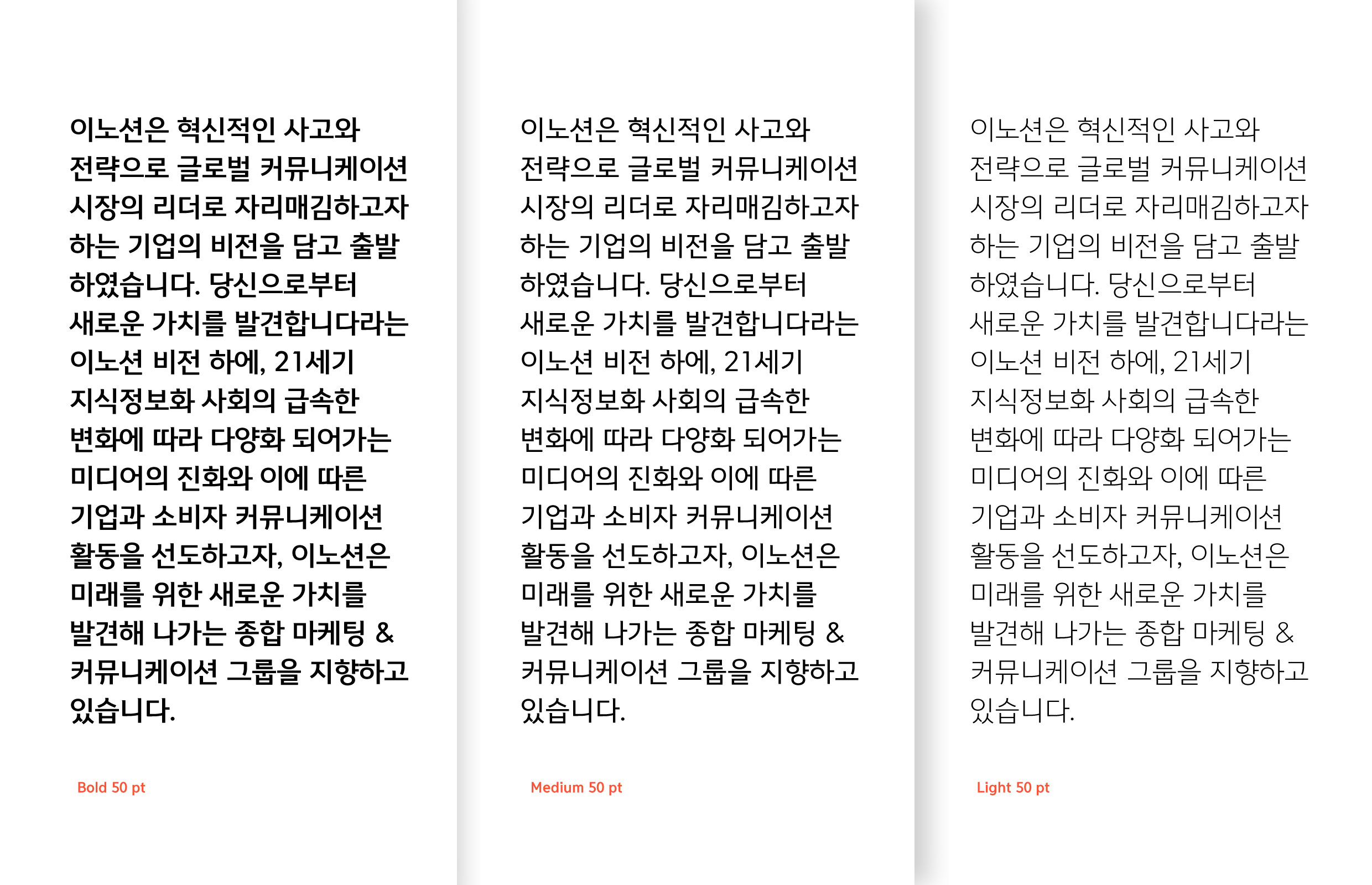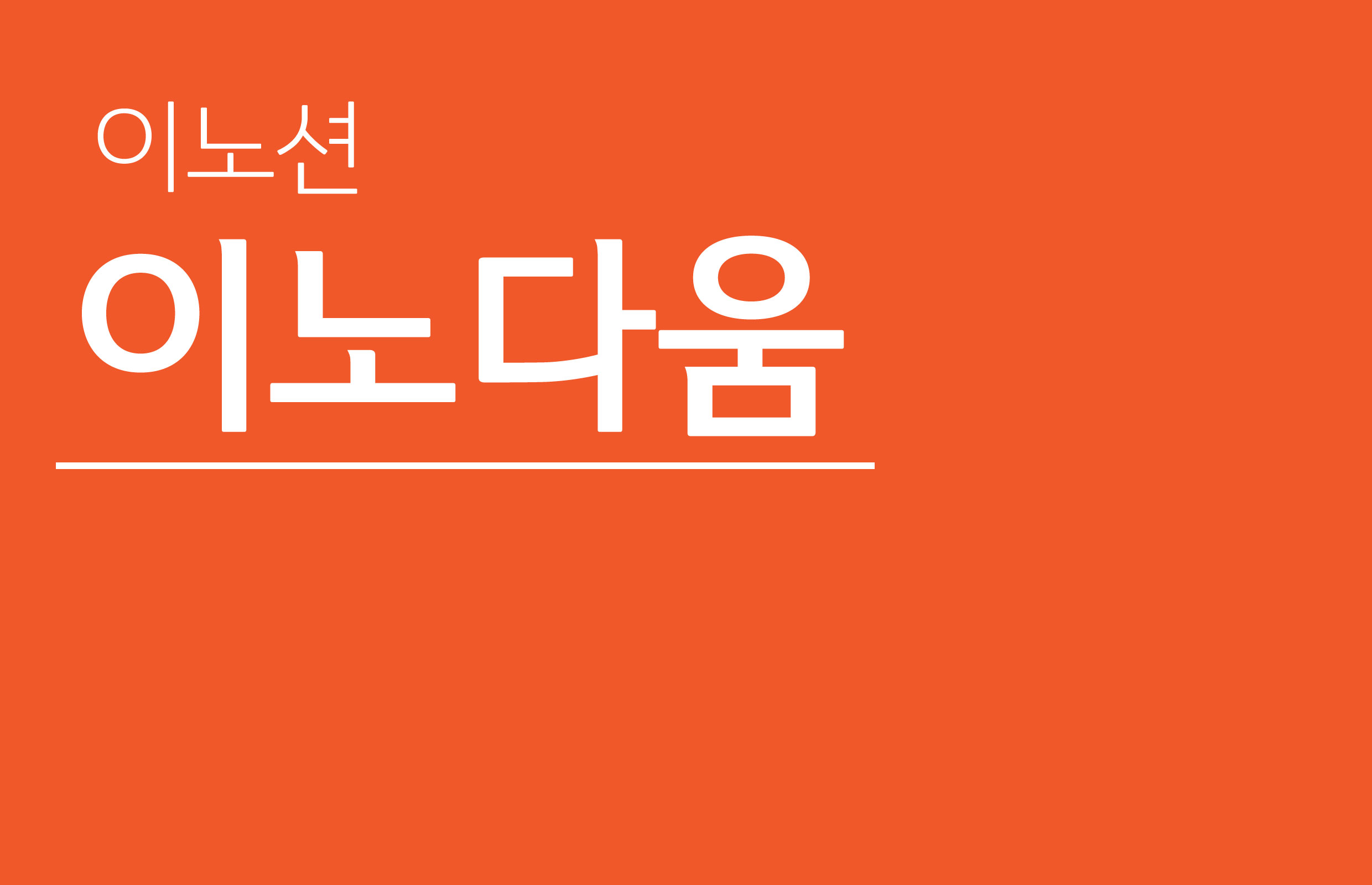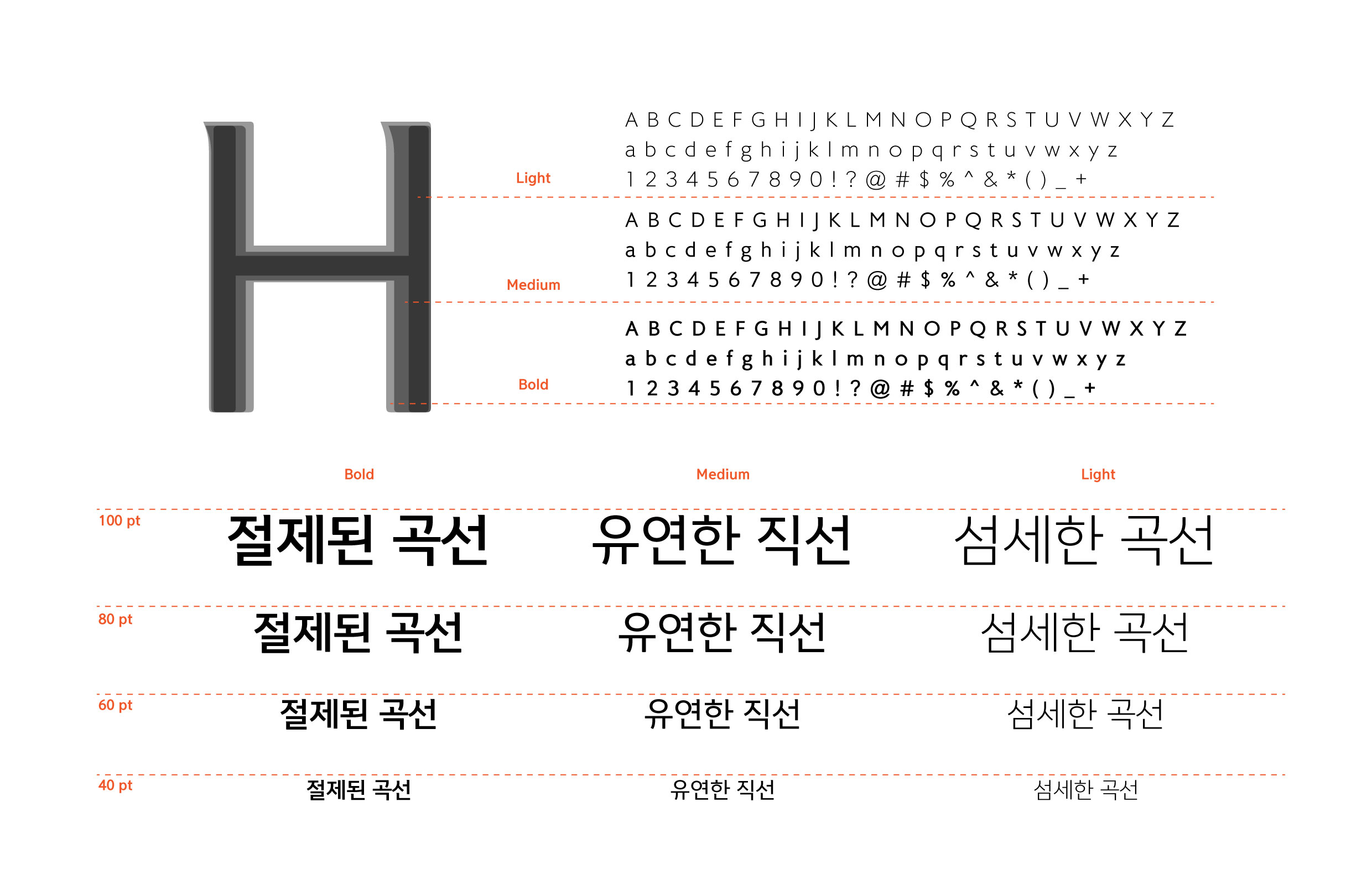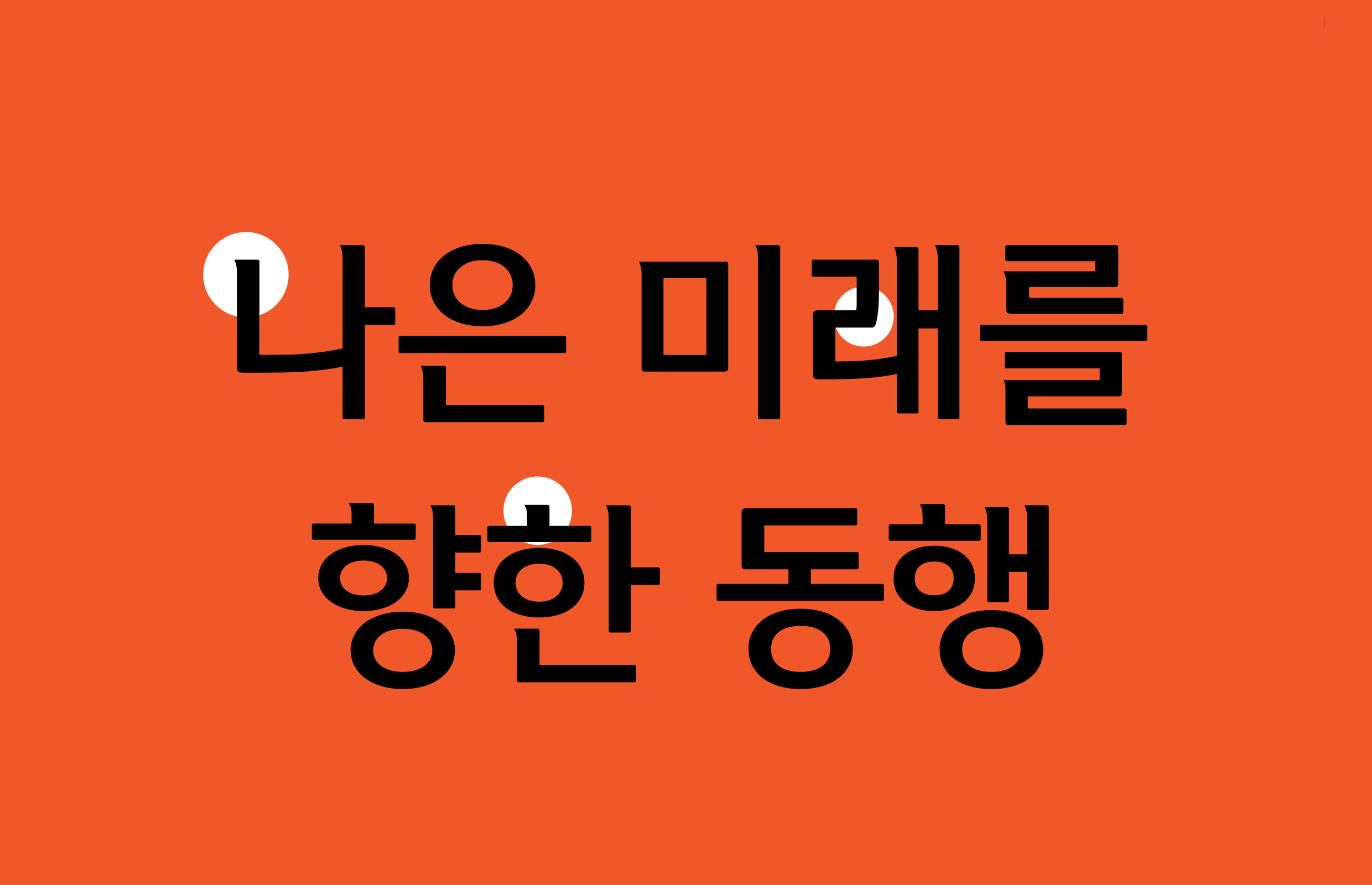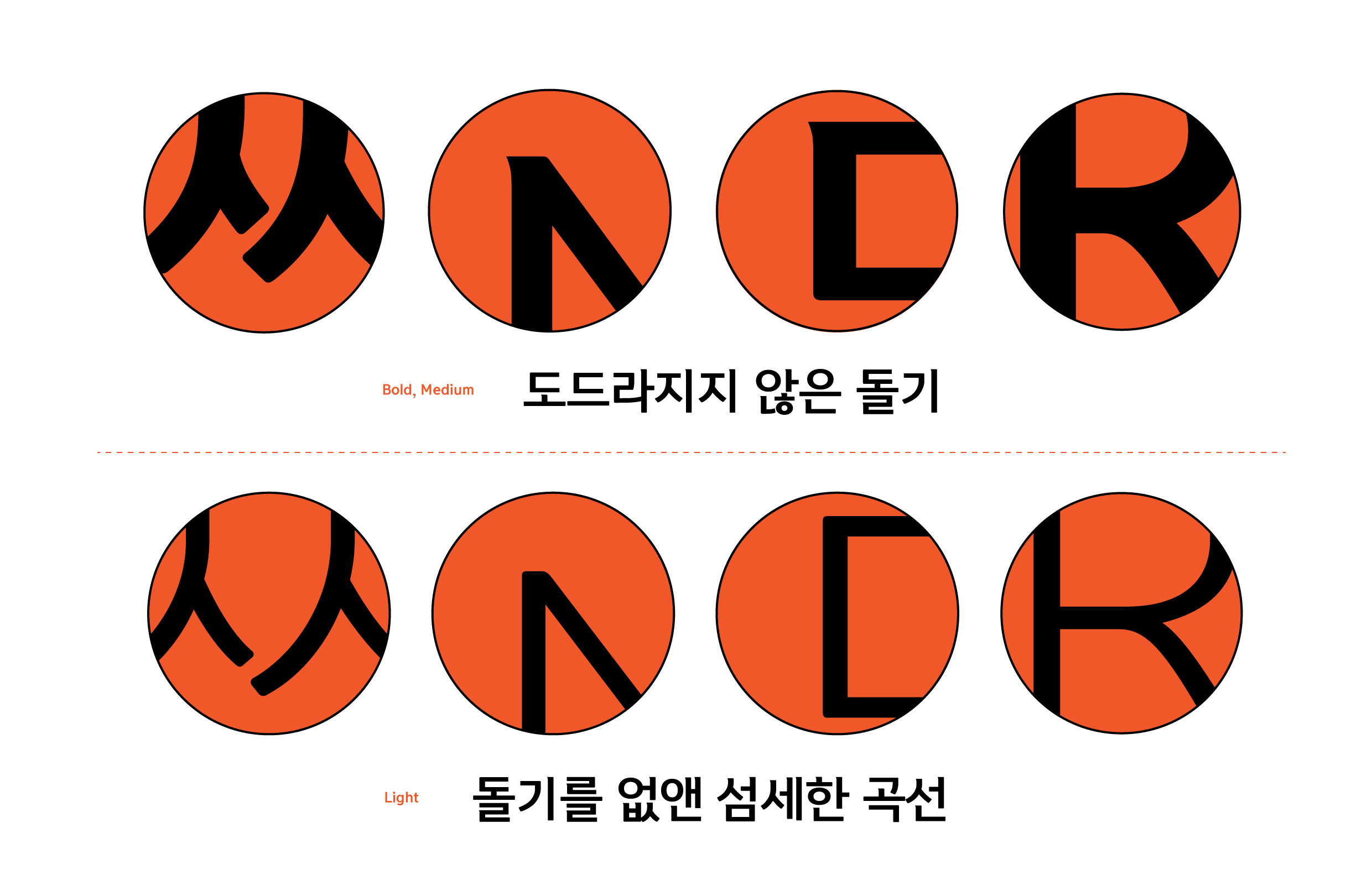
이노션
이노션 [이노다움]
이노션의 브랜드 슬로건인 ‘창조적 도전 정신, 새로운 개성, 혁신적 소통’을 절제된 곡선과 유연한 직선의 조화로 전용서체에 담았다. 도드라지지 않은 돌기는 외유내강형 전문인을 상징하고, 정통성을 반영한 자소 디자인은 이노션만의 개성과 엣지를 의미한다.